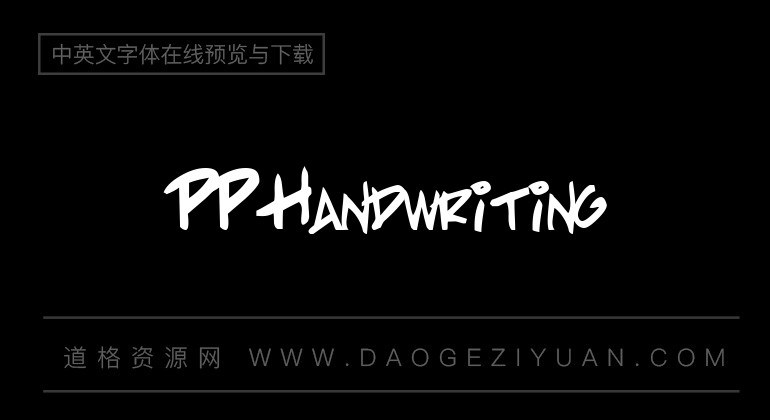
? PP Handwriting 是一款拥有温暖、清新风格的手写字体,它非常适合用于创意设计、海报、海报、海报、婚礼、派对、婚礼邀请函、朋友圈等。它具有温暖、清新的手写风格,极具设计感,可以让你的作品更加有质感。PP Handwriting 字体拥有更细腻的笔画,让你的文字更加清晰,而且可以让你的文字更加有质感。内容介绍
PP Handwriting是一款非常不错的手写艺术字体,具有很好的视觉感,适合于文化类的宣传设计、商业类品牌的广告和产品包装设计以及个性化文字排版等较多场景。